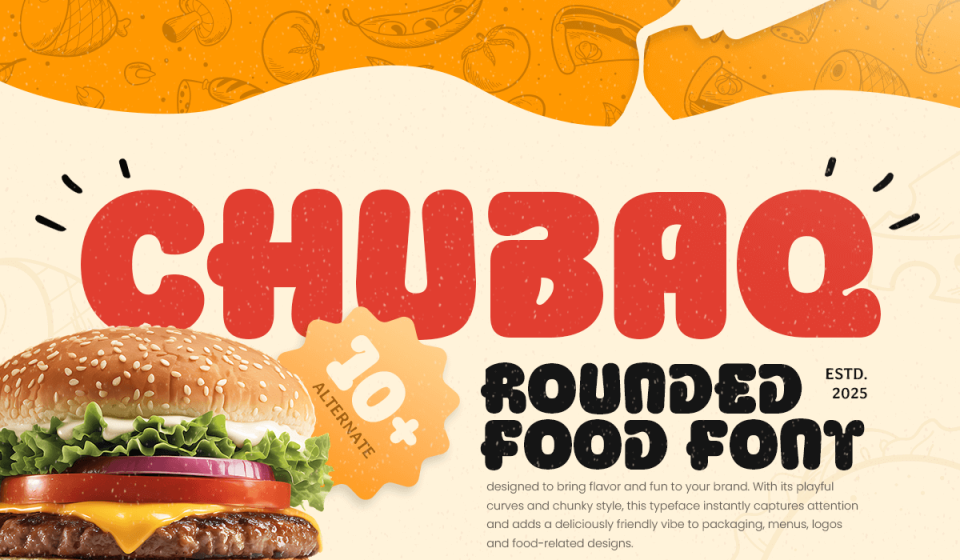
فونت Chubaq – تایپفیس برندینگ صنایع غذایی و رستوران
فونت Chubaq – تایپفیس گرد، جذاب و اشتهاآور برای برندینگ صنایع غذایی و رستوران
در طراحی هویت بصری برای مواد غذایی، فونت شما باید به اندازه خود محصول وسوسهانگیز باشد. فونت فانتزی برای صنایع غذایی مدل Chubaq، یک تایپفیس گرد و “تپل” است که برای تزریق جذابیت و انرژی دوستانه به پروژههای خلاقانه شما طراحی شده است. این فونت با منحنیهای نرم و فرمهای اشتهابرانگیز، انتخابی ایدهآل برای برندینگ فود، بستهبندی تنقلات، هویت بصری رستورانها و طرحهای تبلیغاتی شاد است. 🍔🍭
Chubaq به گونهای طراحی شده که حسی گرم و دعوتکننده را به مخاطب منتقل کند. فونت انگلیسی گرد برای منو و بستهبندی Chubaq با زیباییشناسی جسورانه اما نرم خود، به خوبی در منوها، پوسترها، محصولات کودک و لیبل محصولات میدرشد. ساختار دایرهای و نرم هر حرف، باعث میشود متن شما ظاهری لذیذ و بصری دلپذیر پیدا کند؛ ابزاری مقتدر برای طرحهایی که به شخصیت و “طعم” نیاز دارند. ✨🍟
ویژگیهای کلیدی و برجسته فونت Chubaq
این فونت با تمرکز بر جذابیت بصری در دنیای خوشمزهها، ویژگیهای زیر را ارائه میدهد:
- حروف ضخیم و گرد (Bold Rounded): طراحی شده برای ایجاد حس صمیمیت و اشتهاآوری. ✅
- اشکال دوستانه و شاد: فرمهای بصری جذاب که برای محصولات مرتبط با کودکان عالی است. 🧸
- تایپفیس همهکاره: مناسب برای رستورانها، بستهبندی اسنک، منوها و برندینگ فان. 🍕
- خوانایی بالا در عناوین: بهینهسازی شده برای تیترهای درشت پوسترها و گرافیکهای شبکههای اجتماعی. 📱
کاربردهای اصلی فونت Chubaq ⚙️
این تایپفیس برای پروژههایی که به دنبال ظاهری شاد و وسوسهانگیز هستند، گزینهای مقتدر است:
- طراحی لوگو برای فستفودها، کافیشاپها و برندهای شیرینی و شکلات 🍩
- طراحی بستهبندی مواد غذایی، چیپس، پفک و خوراکیهای هیجانانگیز 🍿
- خلق منوهای مدرن و فانتزی برای رستورانهای با کانسپت خلاقانه 📋
- تولید محتوای تبلیغاتی برای اینستاگرام و کمپینهای مارکتینگ غذا 📸
- طراحی پوسترها و بیلبوردهای محیطی برای محصولات جدید صنایع غذایی 🖼️
- شامل حروف بزرگ (Uppercase)، حروف کوچک (Lowercase)، اعداد و علائم نگارشی
- پشتیبانی از ویژگیهای OpenType برای انعطاف بیشتر در طراحی تایپوگرافی
نکته مهم: فونت Chubaq قدرت خود را در استفاده از رنگهای گرم و زنده (مانند قرمز، نارنجی و زرد) نشان میدهد. ترکیب این فونت با سایههای نرم یا استایلهای “حبابی” میتواند جذابیت بصری طرح شما را برای مخاطب چندین برابر کند.